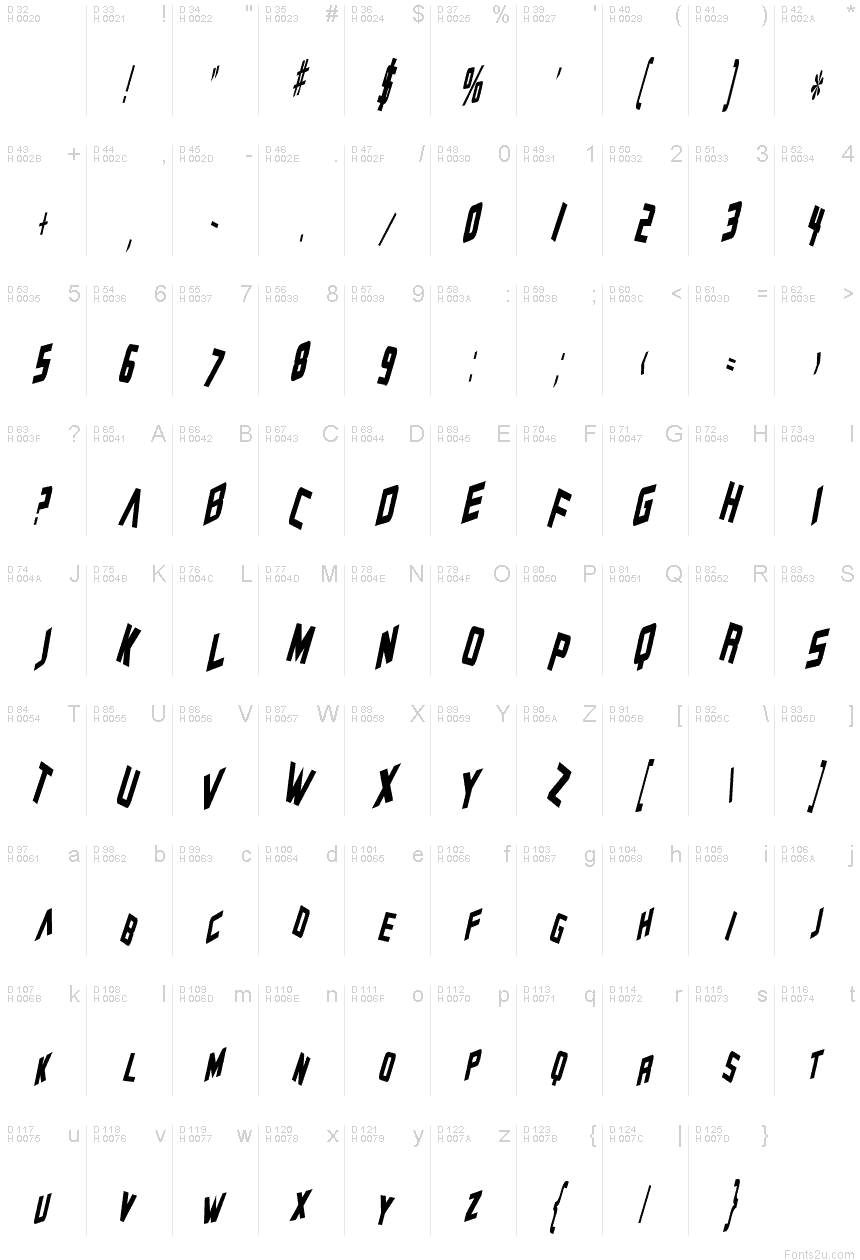
Zero Gravity Italic von ShyWedge ist eine kostenlose, kursive Sci-Fi-Display-Schrift mit einer scharfen, schwerelosen Neigung und einer Ästhetik wie aus Scherenschnitten. Die Buchstaben wirken in kantige Keile gehauen und kombinieren geneigte Striche, spitze Verbindungen und eine unebene Geometrie zu einem Look, der eher an das Space-Branding der späten 90er Jahre erinnert als an glatten Futurismus.
Sie passt perfekt zu Poster-Überschriften, Gaming-Logos, Zine-Covern, Titelseiten und Club-Flyern, wo eine kostenlose Schrift Dynamik verleihen soll, ohne dabei zu poliert zu wirken. Verwenden Sie sie, wenn die Großbuchstaben in der Luft schweben und leicht instabil wirken sollen – besonders bei kurzen Wörtern, Cover-Zeilen oder Monogrammen, die ihre hakenförmigen Ecken und die übertriebene Neigung optimal zur Geltung bringen.